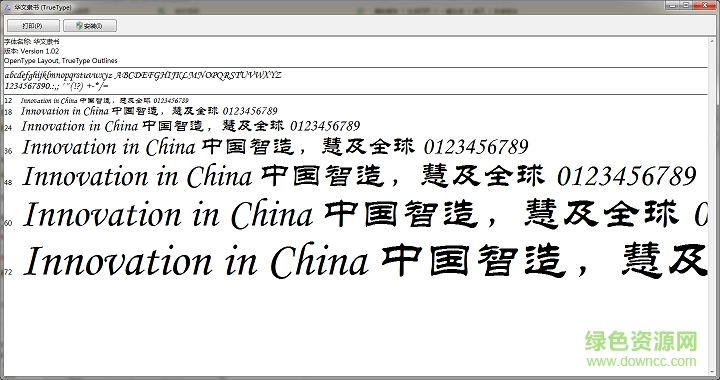
隸書普通gb2312字體
隸書chinese gb2312字體是一款普通的隸書字體,扁方工整,字形規(guī)范,氣質(zhì)莊重,剛?cè)岵?jì),表現(xiàn)力十分豐富,有需要者快來(lái)綠色資源網(wǎng)下載吧!
隸書發(fā)展特點(diǎn)
魏晉以后的書法,草書、行書、楷書迅速形成和發(fā)展,隸書雖然沒(méi)有被廢棄,但變化不多而出現(xiàn)了一個(gè)較長(zhǎng)的沉寂期。到了清代,在碑學(xué)復(fù)興浪潮中隸書再度受到重視,出現(xiàn)了鄭燮、金農(nóng)等著名書法家,在繼承漢隸的基礎(chǔ)上加以創(chuàng)新。
隸書普通gb2312字體
隸變體介紹
變體隸書,又叫隸變體。是當(dāng)代書法流行的隸書風(fēng)格,是針對(duì)傳統(tǒng)隸書而言的書寫注重變化,注重個(gè)性的書寫方式。筆畫不重規(guī)范,強(qiáng)調(diào)即興創(chuàng)作。